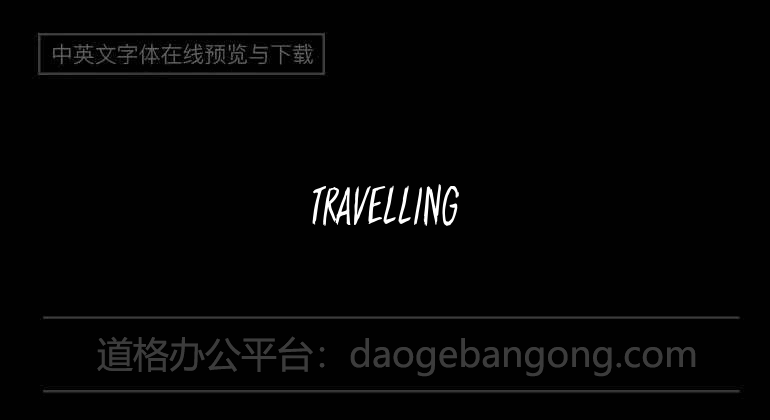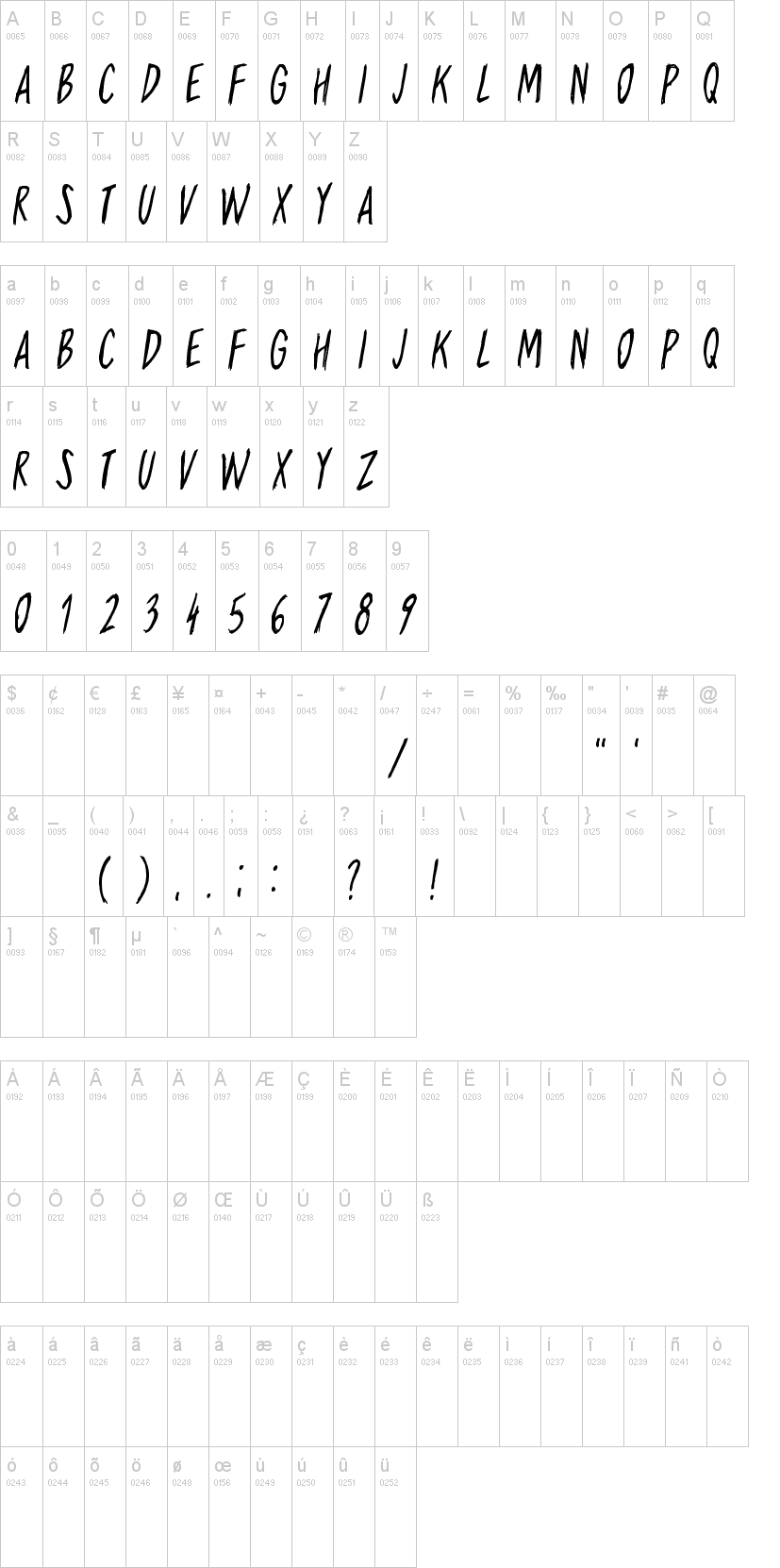
Travelling 是一款由 Fontfabric 公司设计的手写体字体,它的字体特点是字体自然、清新、活泼,可以很好地表达出游记的气氛。它的字体拥有丰富的符号,可以支持多种语言,并且可以做到比较自然的排版。Travelling 字体拥有不同的字重,可以满足各种设计需求,比如海报、横幅、标识等。内容介绍
Travelling是一款非常不错的手写艺术字体,具有很好的视觉感,适合于文化类的宣传设计、商业类品牌的广告和产品包装设计以及个性化文字排版等较多场景。